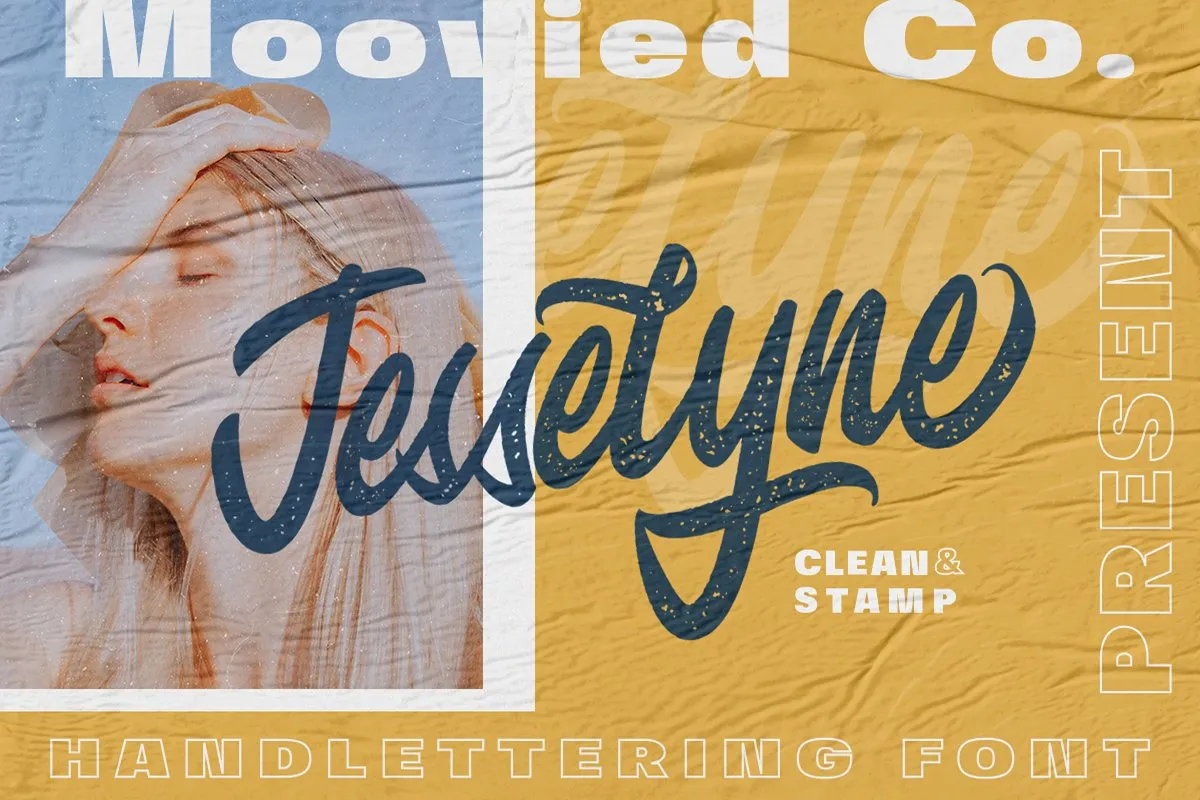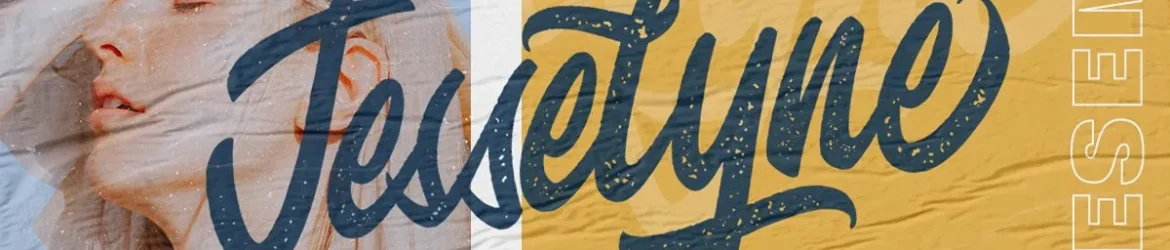
Jesselyne Script Font – Download Grátis
Descubra uma nova fonte script chamada Jesselyne Script Font, criada por Moovied Co., para designers e artesãos apaixonados por estilo urbano, streetwear e vintage. Este belo conjunto de letras é perfeito para uma ampla variedade de projetos, desde logotipos e materiais promocionais até ilustrações e design editorial. Desenvolvida com um estilo delicado de letra contínua conhecido como “handlettering”, Jesselyne Script oferece dois pesos: Regular e Bold. Seu design é ideal para branding, logos, desenhos a mão livre em citações de produtos, embalagens, cabeçalhos, outdoors, materiais promocionais, merchandising, redes sociais, capas de livros ou títulos de eventos especiais. Com sua inspiração em uma mistura de urbanidade e vintage, Jesselyne Script é um complemento perfeito para qualquer projeto que busque incorporar um toque único e sofisticado ao design. Não importa o tipo de projeto em que você esteja trabalhando, essa fonte pode transformá-lo.